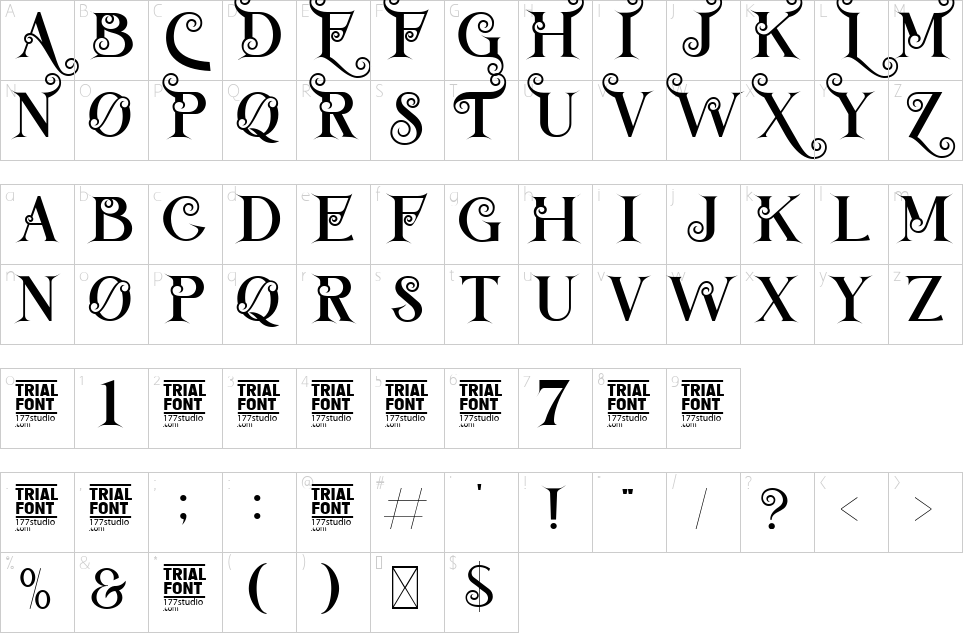
Aproveite para explorar a beleza do ‘Daesang Brothers Font’, uma fonte cuidadosamente criada pela equipe de 177Studio.com. Esta font é perfeitamente adaptada tanto para uso no seu computador Windows quanto na plataforma Mac, tornando-a uma opção versátil para designers e amantes da arte gráfica. Com apenas 2,126 downloads, já é claro que a ‘Daesang Brothers Font’ tem se destacado por sua elegância e variedade de estilos, proporcionando um toque único aos seus projetos digitais. Se você procura uma fonte clara e profissional para incorporar em seu trabalho, este pode ser o grande acréscimo que lhe é necessário. Sua adoção garantirá um acabamento impecável aos seus projetos, oferecendo uma experiência de design completa e agradável. Descubra agora mesmo e deixe sua marca mais marcante com esta fonte.